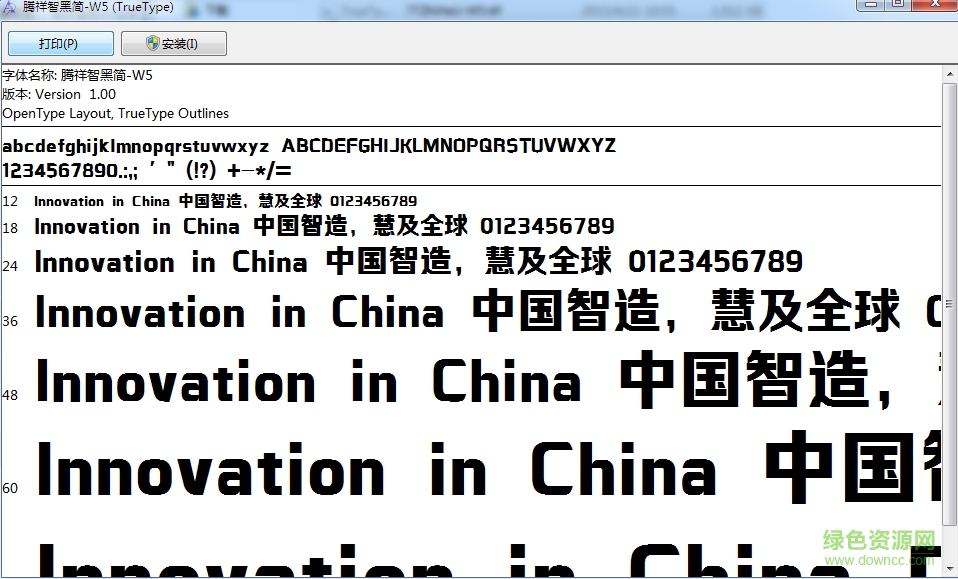
騰祥智黑簡W5字體是一款用于電腦的黑體字體,字體為了調(diào)整黑白空間在筆畫交叉處特別做了墨跡處理,使整體筆畫看起來既粗壯醒目又清晰易讀,喜歡的朋友可以來綠色資源網(wǎng)下載試用!
騰祥智黑-W5為粗黑一款,點形到撇、捺形都做了大膽的創(chuàng)新,塔形頓點、撇點賦予了智黑特殊的設計效果,富于設計感,使智黑又區(qū)別于傳統(tǒng)的黑體。字體粗壯、醒目適用于標題、大標題、海報及大型廣告招貼等。